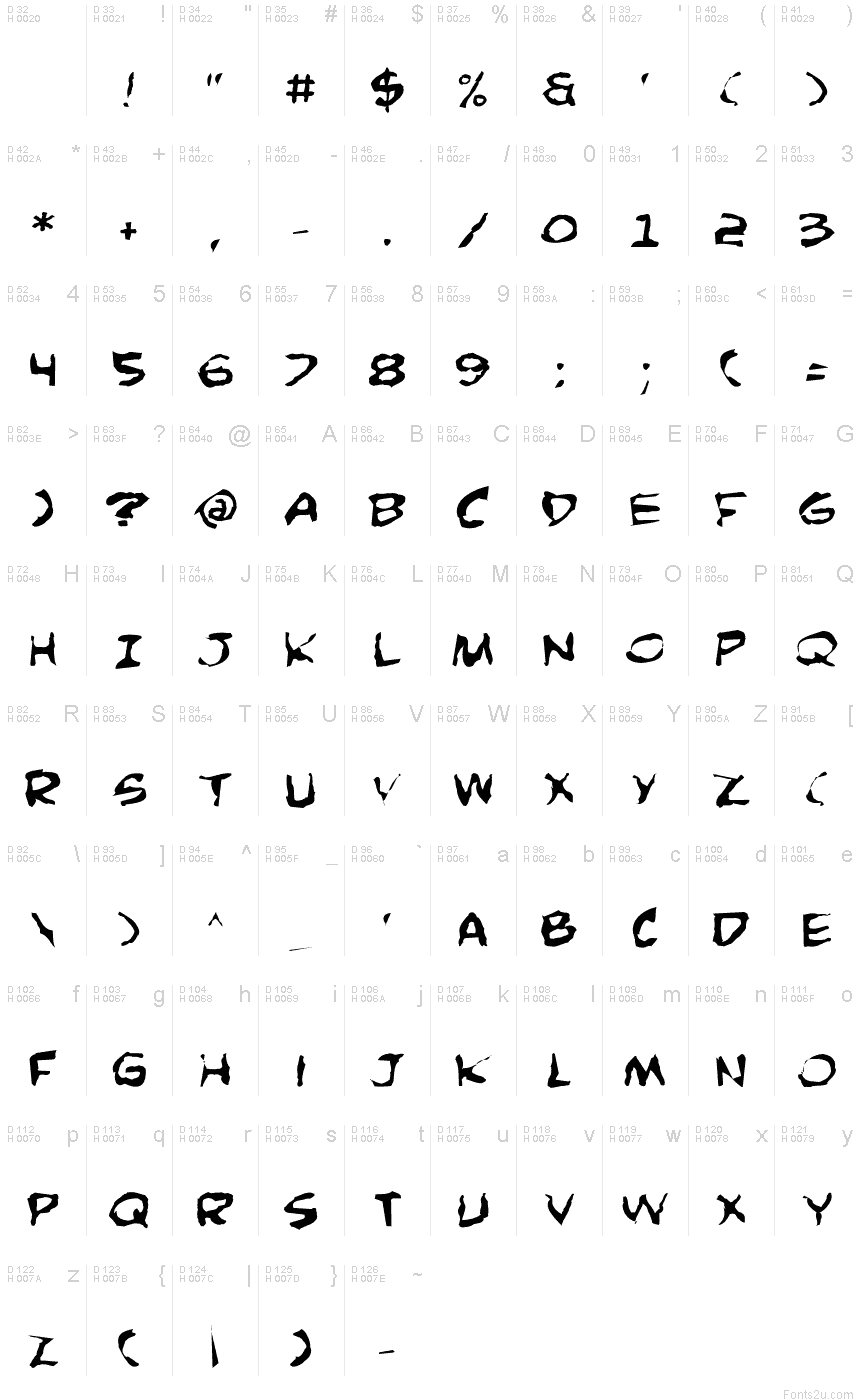
Comic Book Commando Distorted od Iconian Fonts to darmowy krój pisma w komiksowym, „erodowanym” stylu. Wygląda, jakby odbito go grubą warstwą farby, a potem zdrapano i nadgryziono zębem czasu. Masywne kształty pozostają czytelne, ale szorstkie krawędzie i ubytki w literach dodają całości akcji – zupełnie jak dymek w komiksie po ulicznej bójce.
Świetnie sprawdzi się na okładkach komiksów, w tytułach gier niezależnych, na ulotkach skate’owych lub punkowych, miniaturach na YouTube, wlepkach i surowym merchandise. Stosuj ją w dużym rozmiarze, aby podkreślić teksturę, i łącz z czystym krojem bezszeryfowym, np. Inter lub Helvetica, w tekstach głównych – ten darmowy font robi największe wrażenie, gdy nie musi z niczym rywalizować.